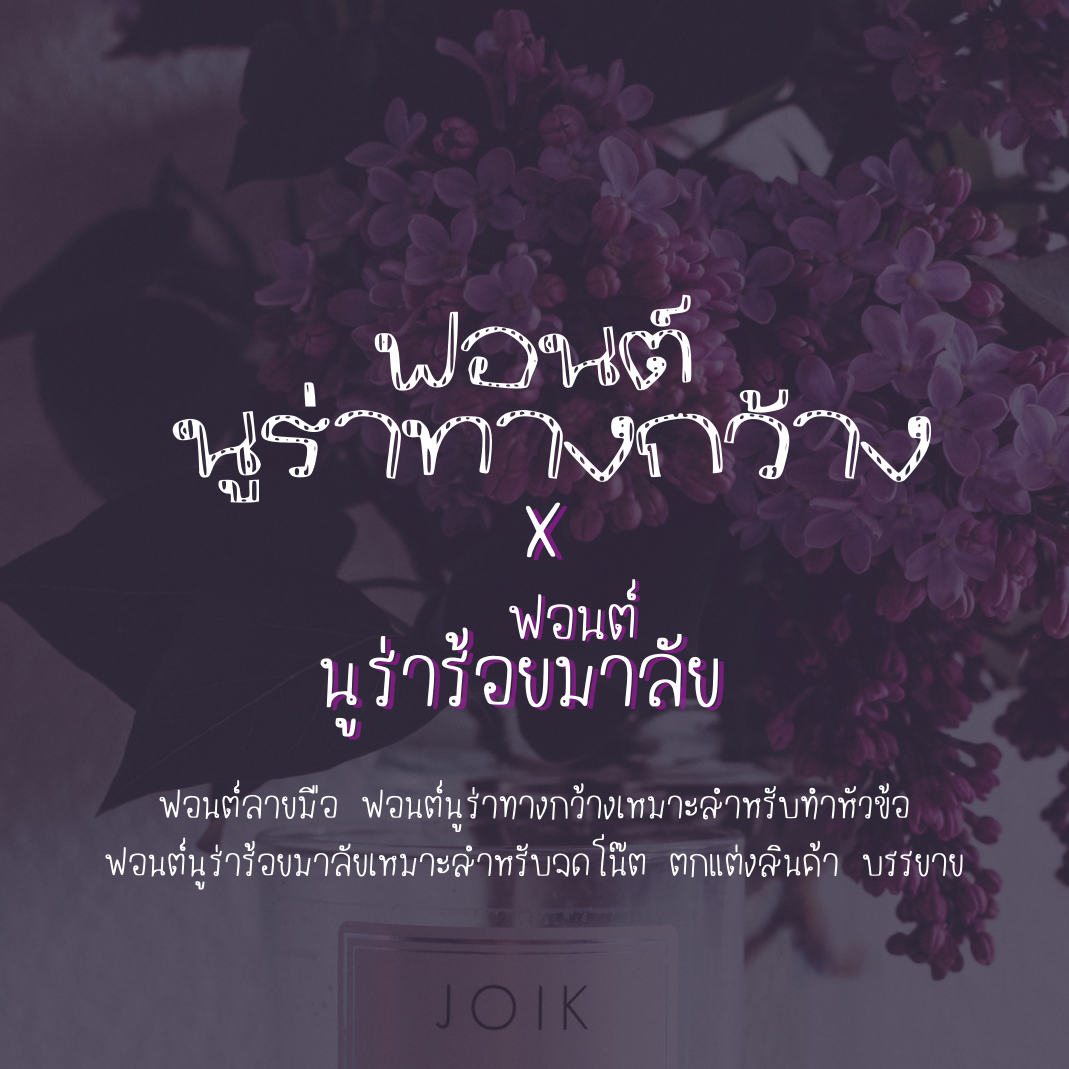
นูร่าทางกว้าง (Nura tangkwang) - นูร่าร้อยมาลัย (Nura roilmalai)
นูร่าทางกว้าง (Nura tangkwang) * นูร่าร้อยมาลัย (Nura roilmalai)
ฟอนต์นูร่าทางกว้าง
ฟอนต์ลายมือสุดวาไรตี้
ดีเทลฟอนต์ตัวกว้าง เป็นลายทาง
ฟอนต์มีด้วยกัน 6 สไตล์ค่ะ  เน้นทำหัวข้อ
ฟอนต์นูร่าร้อยมาลัย ฟอนต์ลายมือตัวเล็ก เส้นบางๆ  ค่อนข้างเรียบร้อย